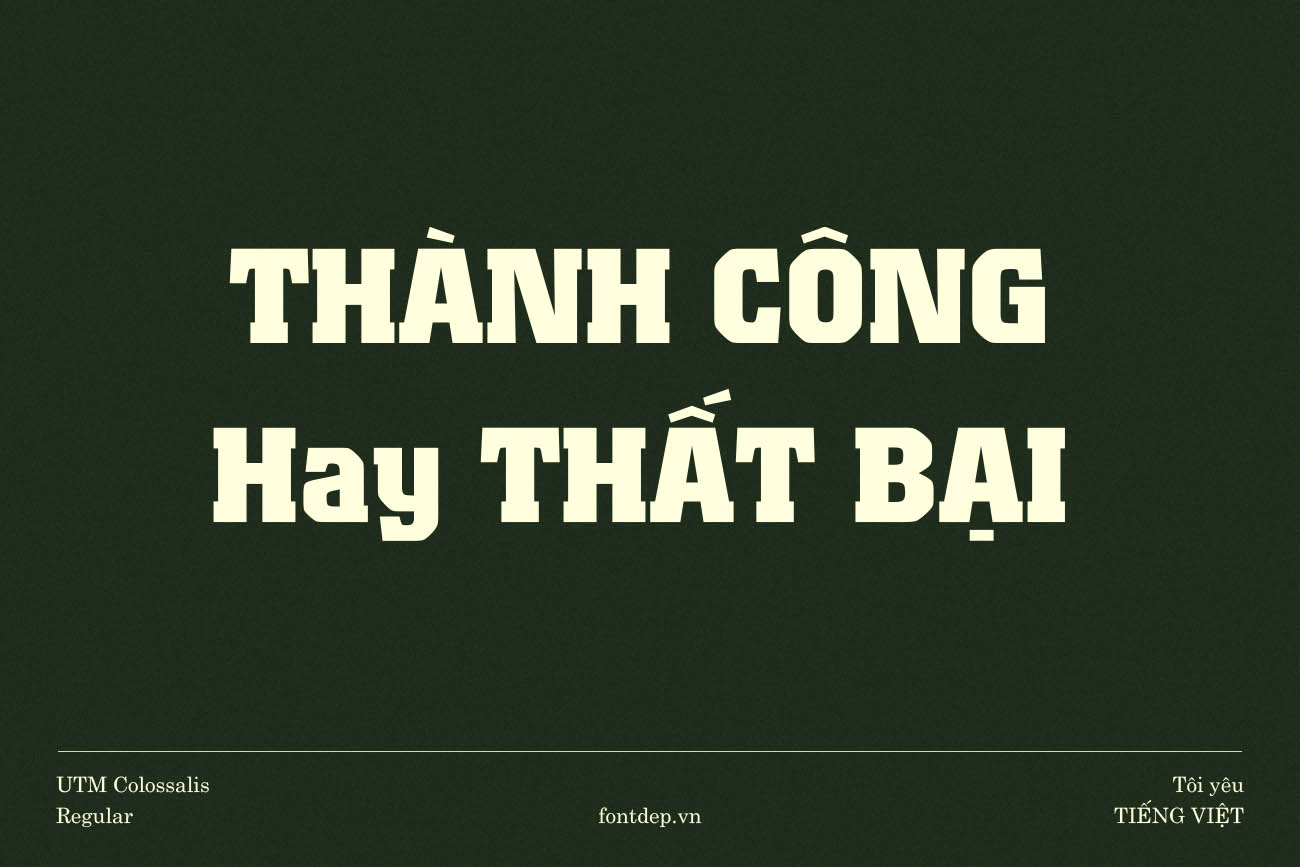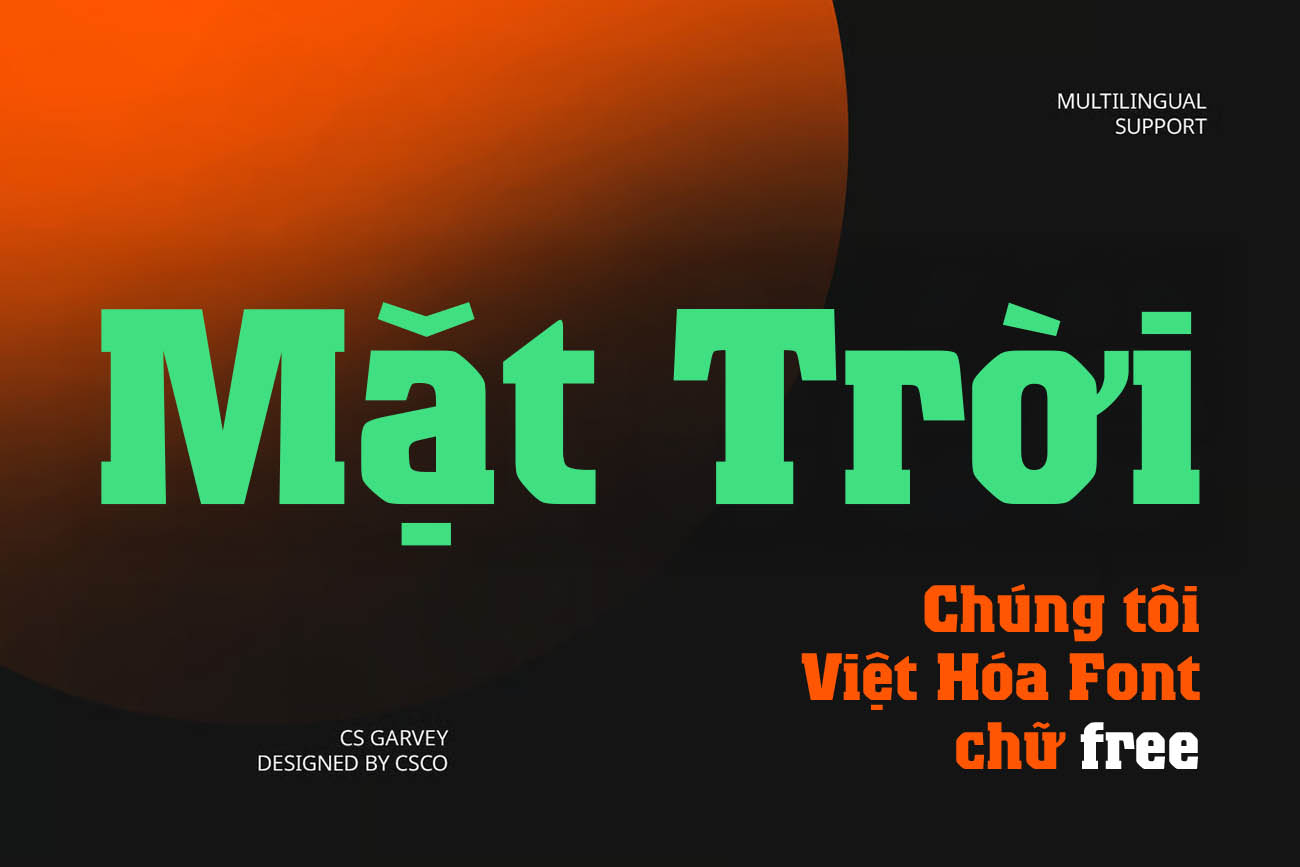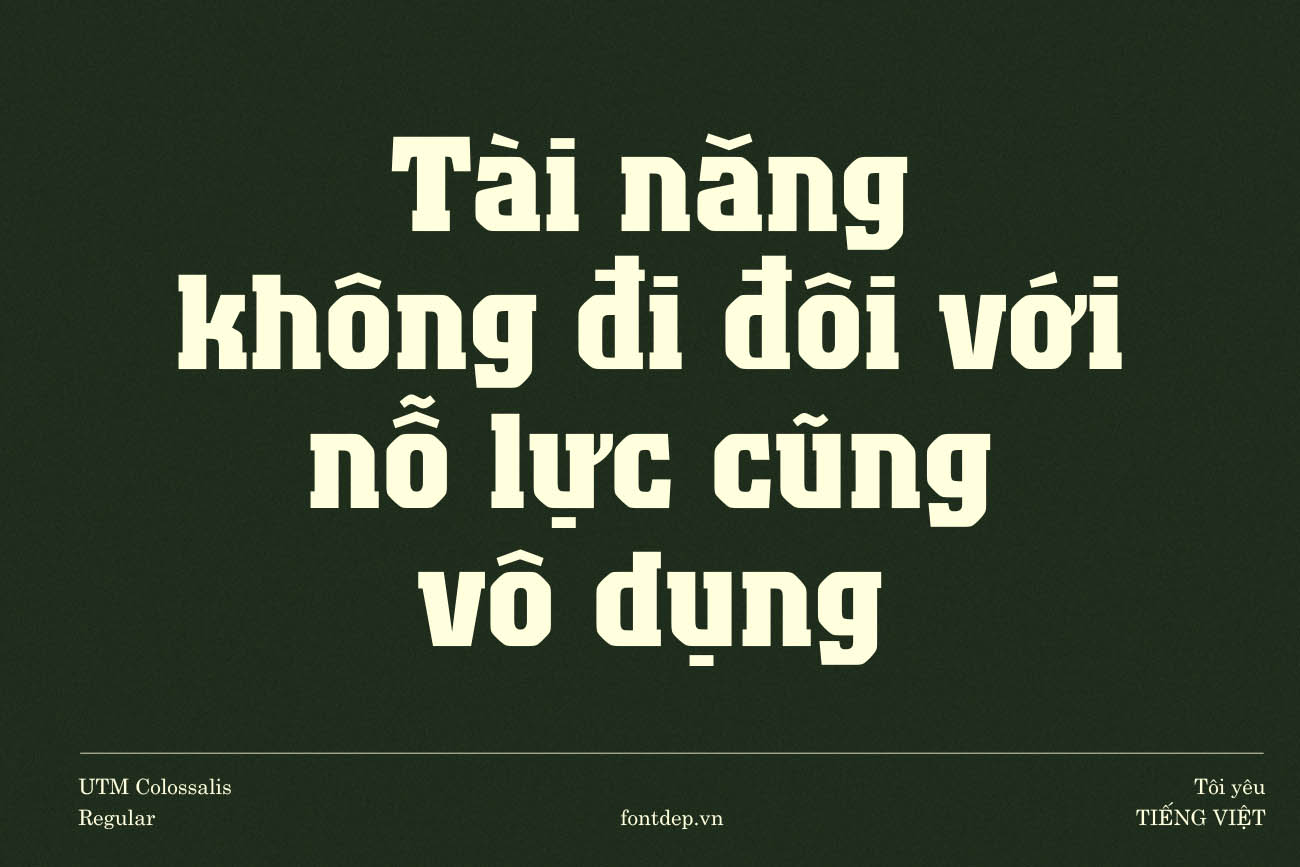
Font Chữ UTM Colossalis Việt Hóa Mạnh Mẽ, Cứng Cáp Miễn Phí
Mỗi dự án sáng tạo luôn cần một bộ chữ phù hợp để làm nổi bật ý tưởng. Nếu bạn đang tìm kiếm kiểu chữ vừa chắc khỏe, vừa dễ đọc và mang đến cảm giác mạnh mẽ, thì UTM Colossalis chính là lựa chọn đáng để cân nhắc.
Nguồn gốc và Việt hóa
Font chữ này được phát triển dựa trên thiết kế gốc CS Garvey (Colossalis) do CSCO – Creative Studio Co. sáng tạo. Điểm đáng chú ý là phiên bản UTM Colossalis Việt Hóa đã được nhóm UTM bổ sung đầy đủ dấu tiếng Việt, đảm bảo sử dụng trọn vẹn cho mọi nội dung, từ ấn phẩm in ấn cho tới thiết kế kỹ thuật số.
Font Chữ UTM Colossalis Việt Hóa – Mạnh Mẽ, Cứng Cáp
Điểm đặc trưng
UTM Colossalis gây ấn tượng nhờ phong cách slab serif hiện đại:
• Nét chữ to bản, vuông vức, mang lại cảm giác vững chắc.
• Chân chữ dày và đều, giúp chữ trở nên nổi bật hơn trong các bố cục lớn.
• Cấu trúc gọn gàng, cân đối, giữ độ dễ đọc ngay cả khi phóng to hoặc thu nhỏ.
• Hỗ trợ đa ngôn ngữ, đặc biệt là tiếng Việt Unicode.
Font Chữ UTM Colossalis Việt Hóa – Mạnh Mẽ, Cứng Cáp
Ứng dụng thực tế
Với ngoại hình chắc nịch và trực diện, font chữ này có thể được dùng cho nhiều loại hình thiết kế:
• Tiêu đề poster, banner sự kiện: tạo sức hút ngay từ ánh nhìn đầu tiên.
• Logo và slogan doanh nghiệp: thể hiện sự bền vững và đáng tin cậy.
• Tạp chí, sách báo, ấn phẩm truyền thông: giữ tính chuyên nghiệp và rõ ràng.
• Quote truyền cảm hứng hoặc thiết kế động lực: làm nổi bật sự quyết tâm và tinh thần mạnh mẽ.
Vì sao nên chọn UTM Colossalis?
Không quá cầu kỳ nhưng lại cực kỳ hiệu quả, UTM Colossalis chinh phục người dùng nhờ khả năng cân bằng giữa tính thẩm mỹ và công năng. Dù bạn làm việc trong lĩnh vực quảng cáo, xuất bản hay thiết kế thương hiệu, font chữ này đều mang lại sự chắc chắn và hiện đại cần thiết để nhấn mạnh thông điệp.